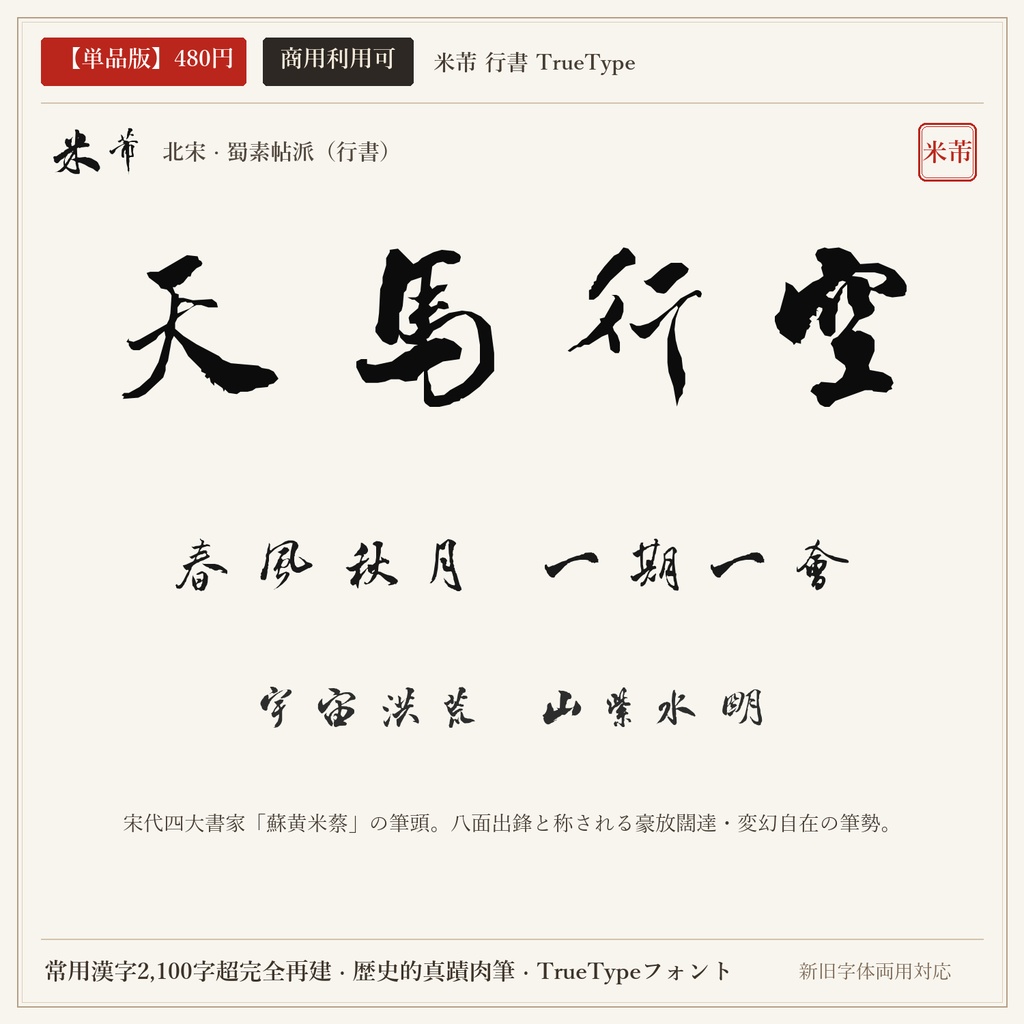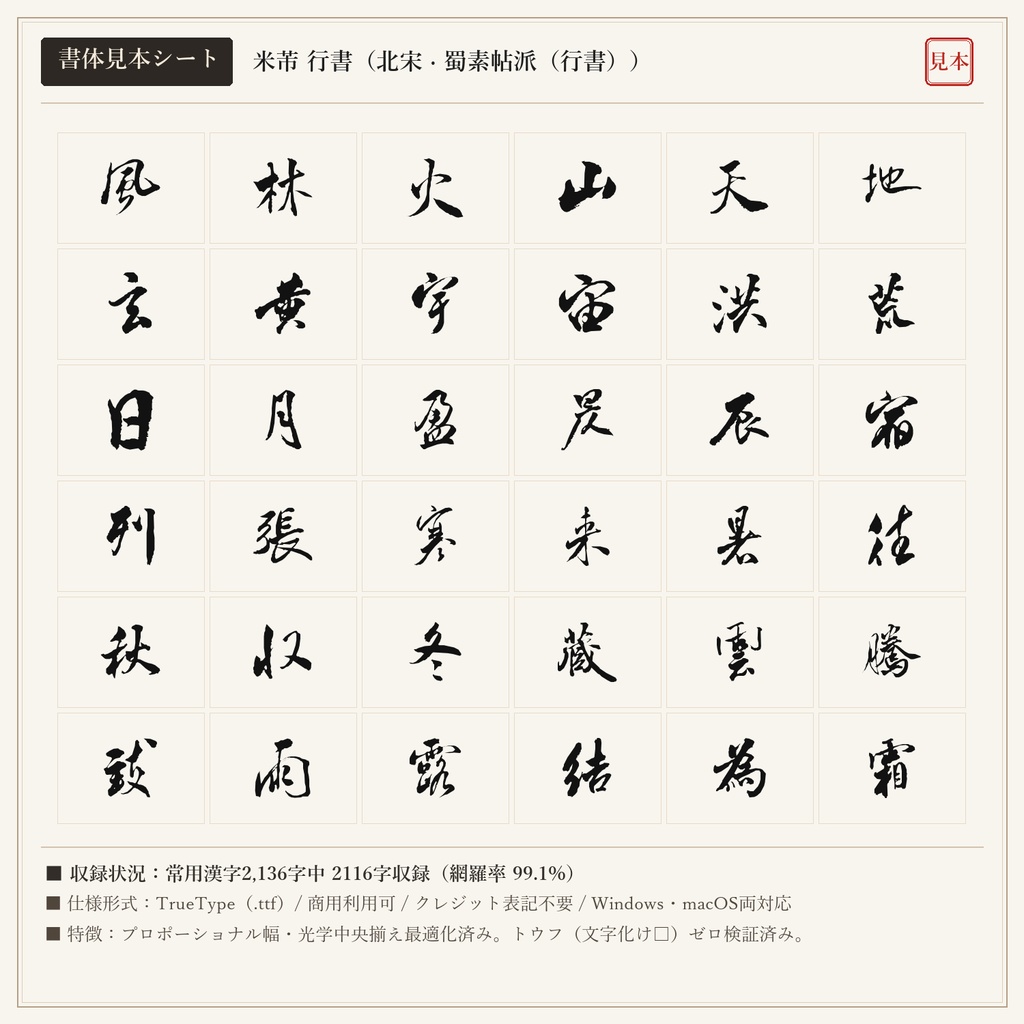
【単品版】米芾 行書フォント|八面出鋒・奇絶躍動の天馬行空・商用利用可
北宋の奇才・米芾(べいふつ)の真蹟遺墨(蜀素帖・苕渓詩帖など)から直接輪郭抽出した行書フォントです。筆の穂先のあらゆる面を縦横無尽に駆使する「八面出鋒」の立体感と疾走感がそのまま宿っています。 ■ 本フォントの特徴 ・常用漢字2,136字中、2116字を高精度収録(網羅率 99.1%)。 ・現代の新字体を入力しても、歴史的な真蹟字形・旧字体が自然に出力されるデュアルマッピング対応。 ・文字ごとの最適なプロポーショナル字幅設定により、自然で流麗な連綿と墨の息遣いを再現。 ・トウフ(文字化け□)を出さない事前フォントマッピング検証済み。 ■ 未収録文字一覧(全20字) 歴史的真蹟・拓本に存在しない以下の字種は未収録(非対応)となります。ご購入前にご確認ください。 丼 刹 咲 唄 堀 峠 拶 枠 栃 桁 濫 疎 線 脊 菓 著 込 郷 闘 駄 ■ 形式 TrueTypeフォント(TTF) / Windows・macOS両対応 ■ 利用規約 個人・法人の商用利用OK。クレジット表記不要。 ロゴ、動画、ゲーム、書籍、同人誌、配信サムネイル、Web、印刷物、グッズ等に自由にご使用いただけます。 フォントファイル自体の再配布・共有・販売・転売は禁止です。 ※東晋の王羲之(行書)と盛唐の顔真卿(楷書)を同梱した「【無料版】王羲之 + 顔真卿 2書体セット(0円)」もショップ内にて無料配布中です。